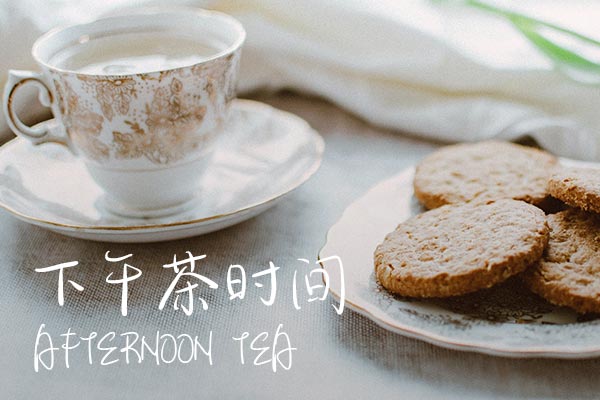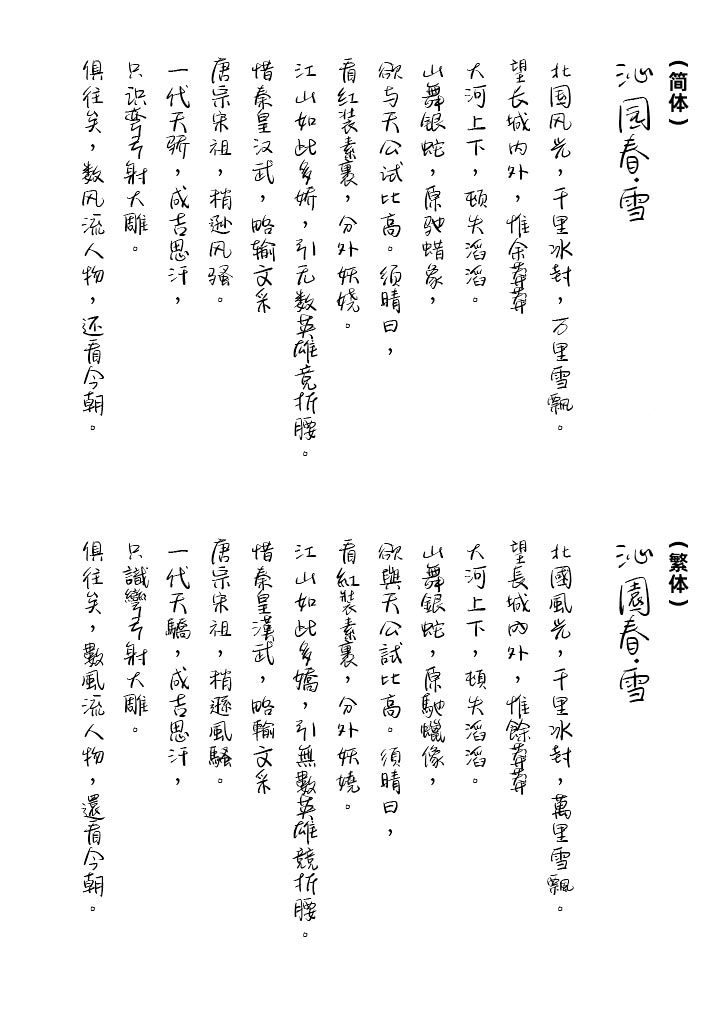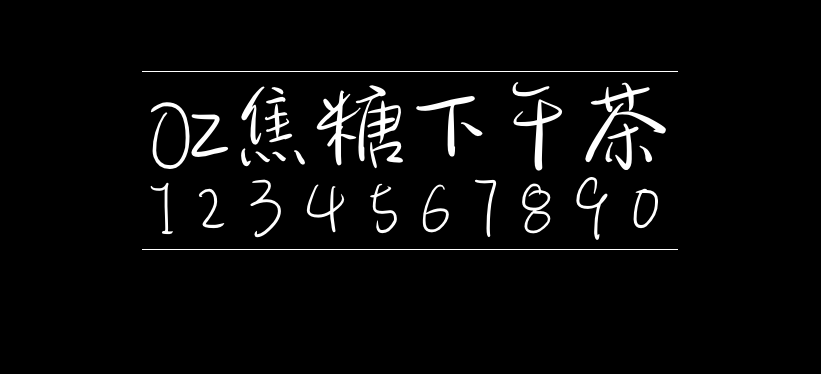
OZ焦糖下午茶
OZ焦糖下午茶是新蒂字体在2020年推出的一款针对个人和小型企业的免费商用字体。OZ焦糖下午茶是一款手写字体,其字形活泼可爱,清秀的字体有着灵动的特质,特别适合小清新,小文艺的设计风格。OZ焦糖下午茶支持超过10000+简体字、繁体字、拉丁字母,字符集已经相当齐全了!
OZ焦糖下午茶